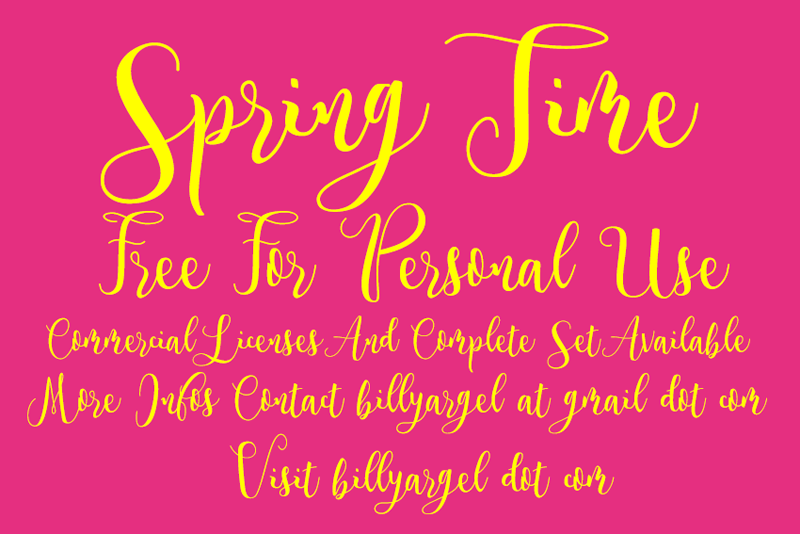
Spring Time Script Font – Download Grátis
A fonte ‘Spring Time Script Font’ é uma grana expressiva para quem procura um acabamento elegante e sofisticado nas criações digitais. Desenvolvida por Billy Argel, esta fonte de calligrafia traz uma textura que reflete a primavera em pleno apogeu — com seus detalhes delicados e movimentos fluidos. Seu estilo serpenteante se ajusta perfeitamente para nomes de marca ou trabalhos de arte que precisam de um toque romântico e versátil, como cartazes, folders corporativos ou até mesmo revistas. Esta fonte é ideal tanto para projetos pessoais quanto para o uso comercial, com as licenças completas disponíveis através do site oficial do designer. Para mais informações sobre os termos de uso da fonte e outros detalhes interessantes, visite o site do Billy Argel ou siga a página no Facebook dedicada às suas fontes. O que você está esperando para adicionar uma nova dimensão ao seu design?